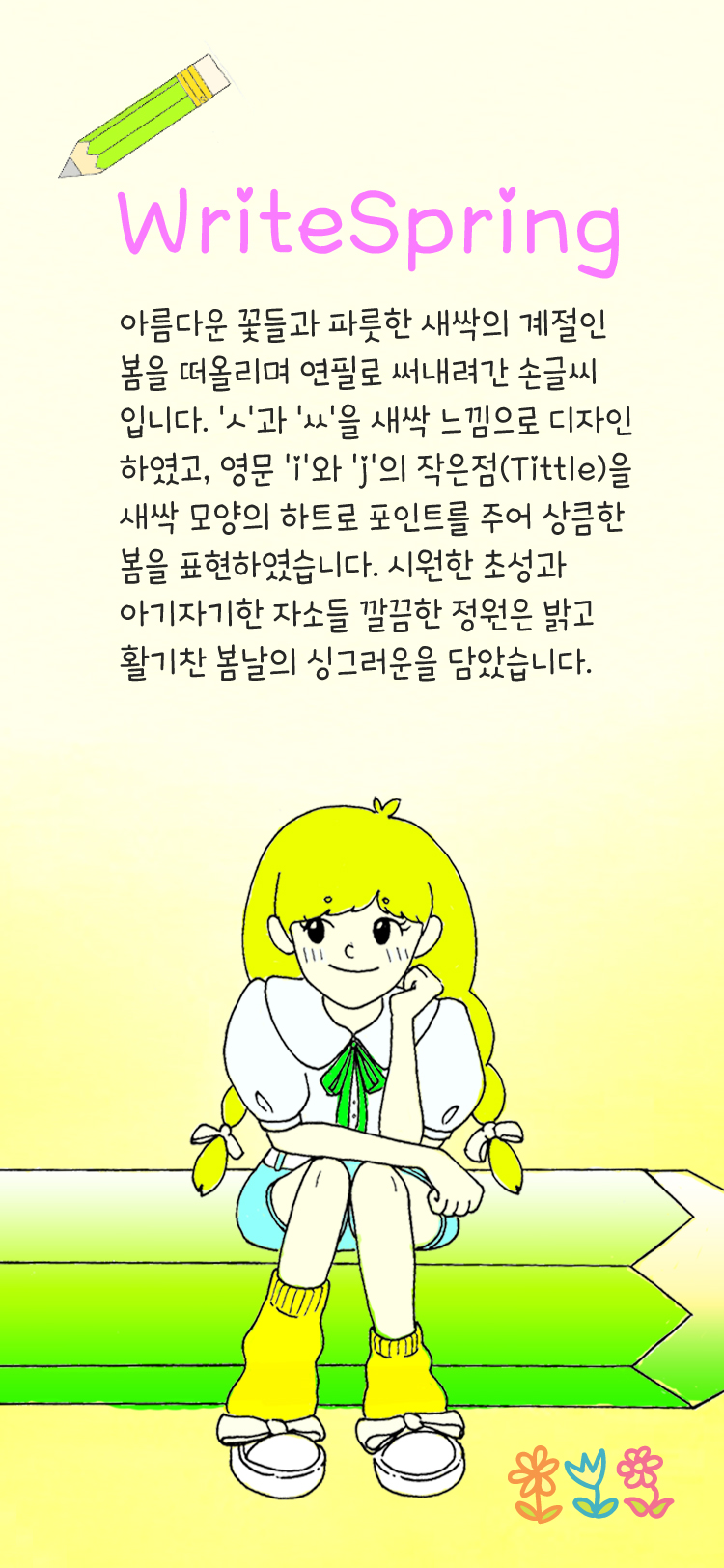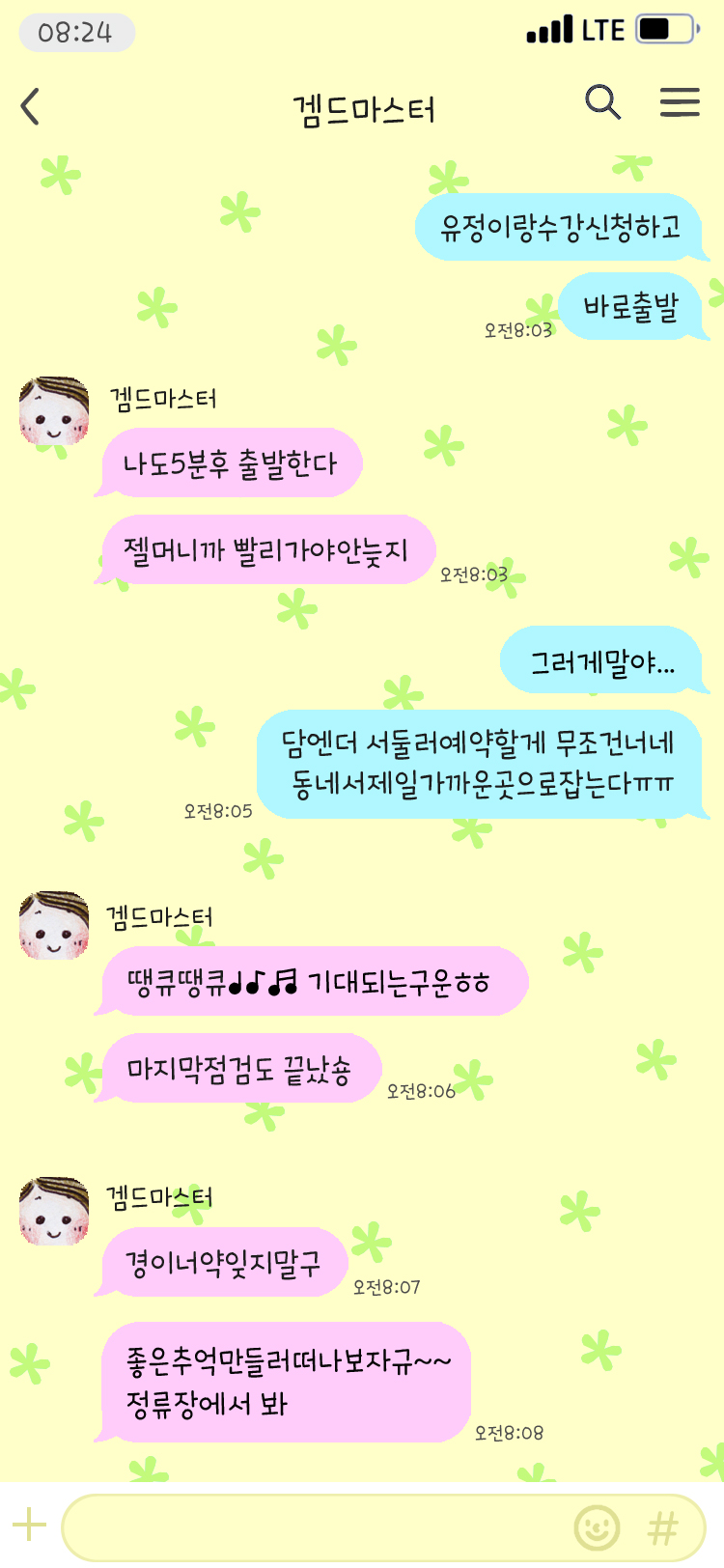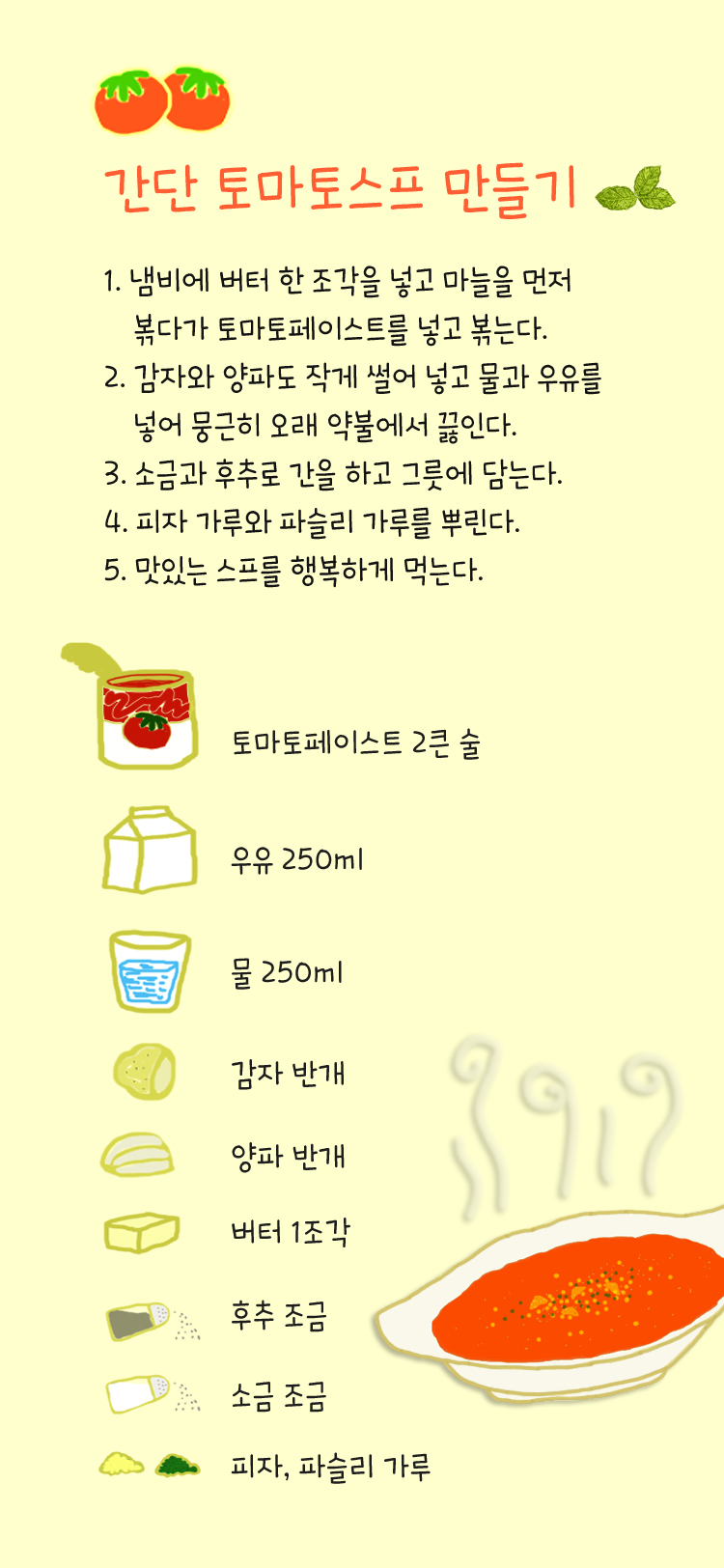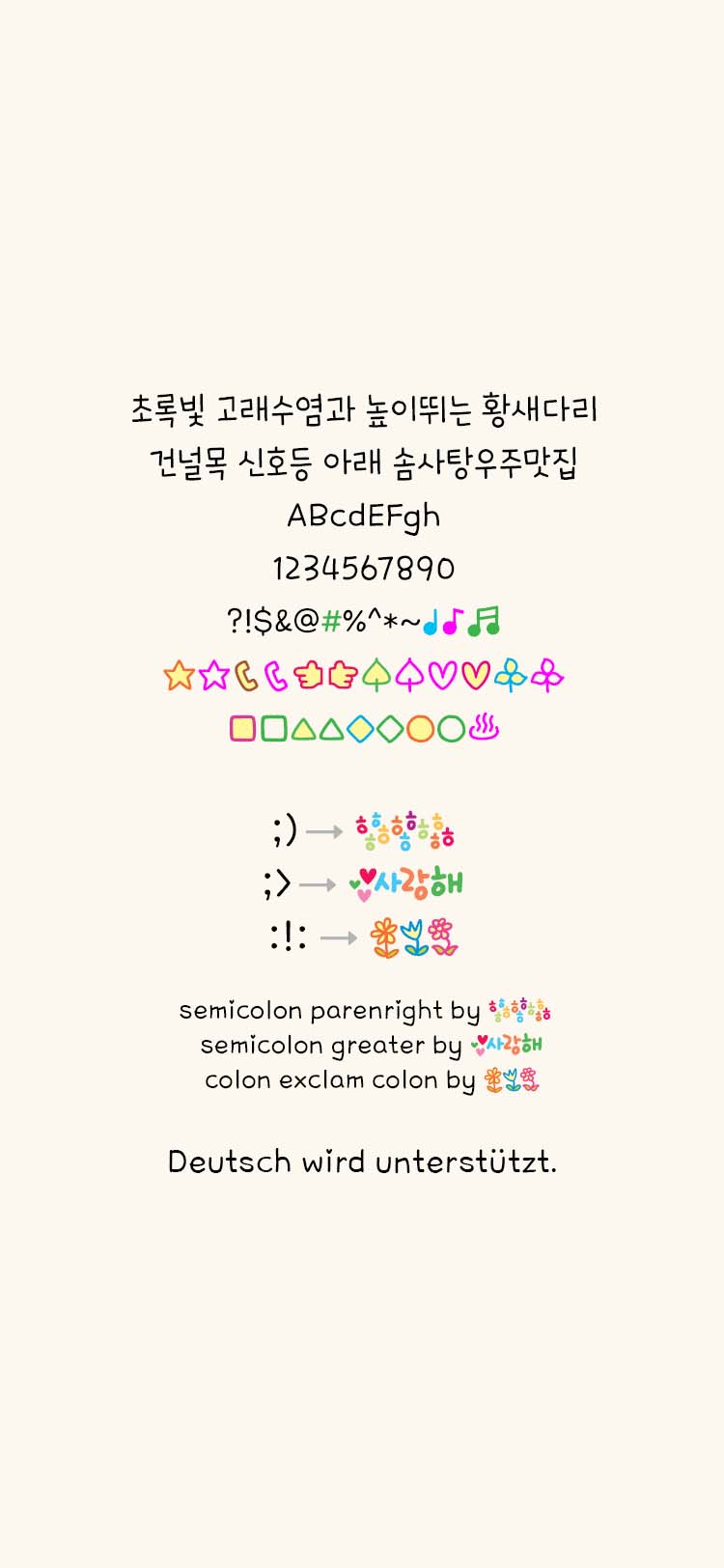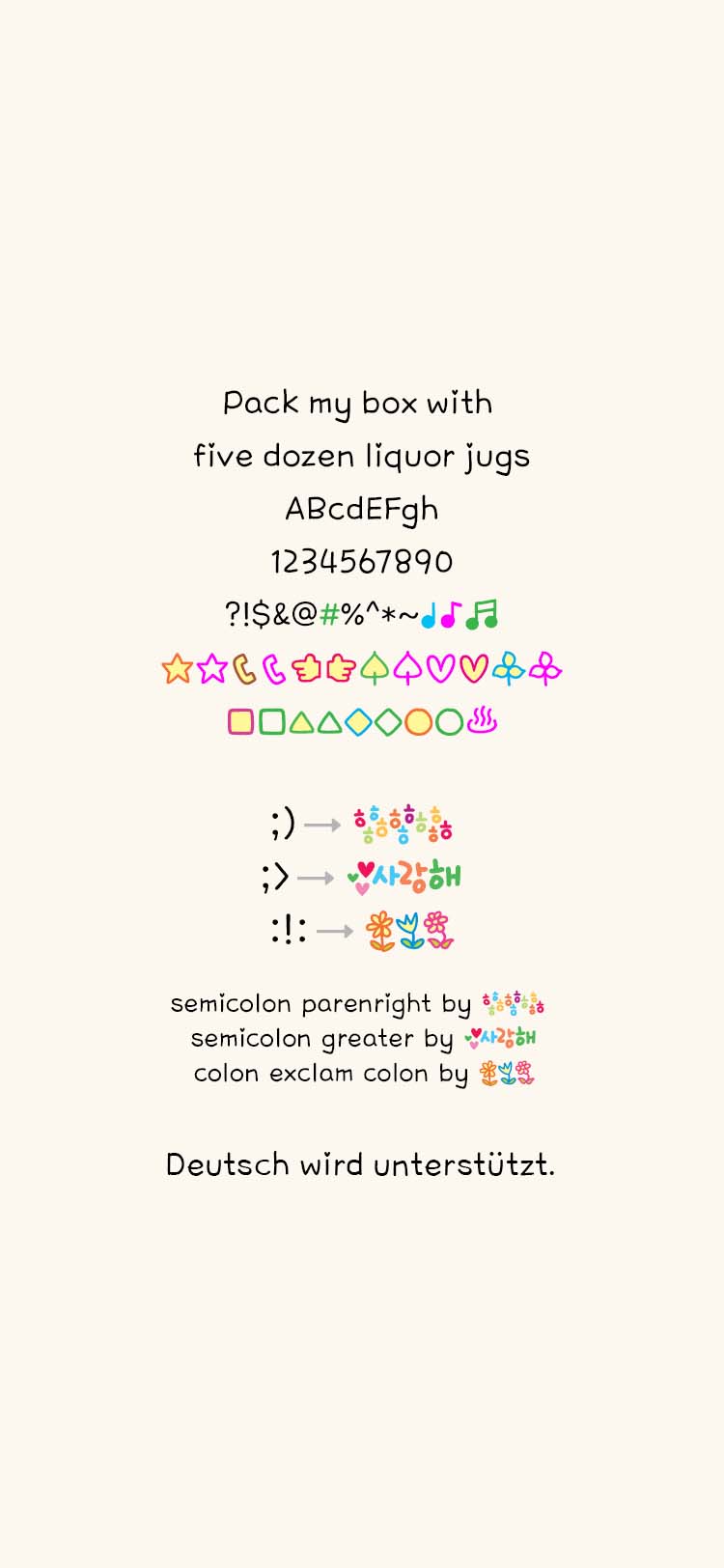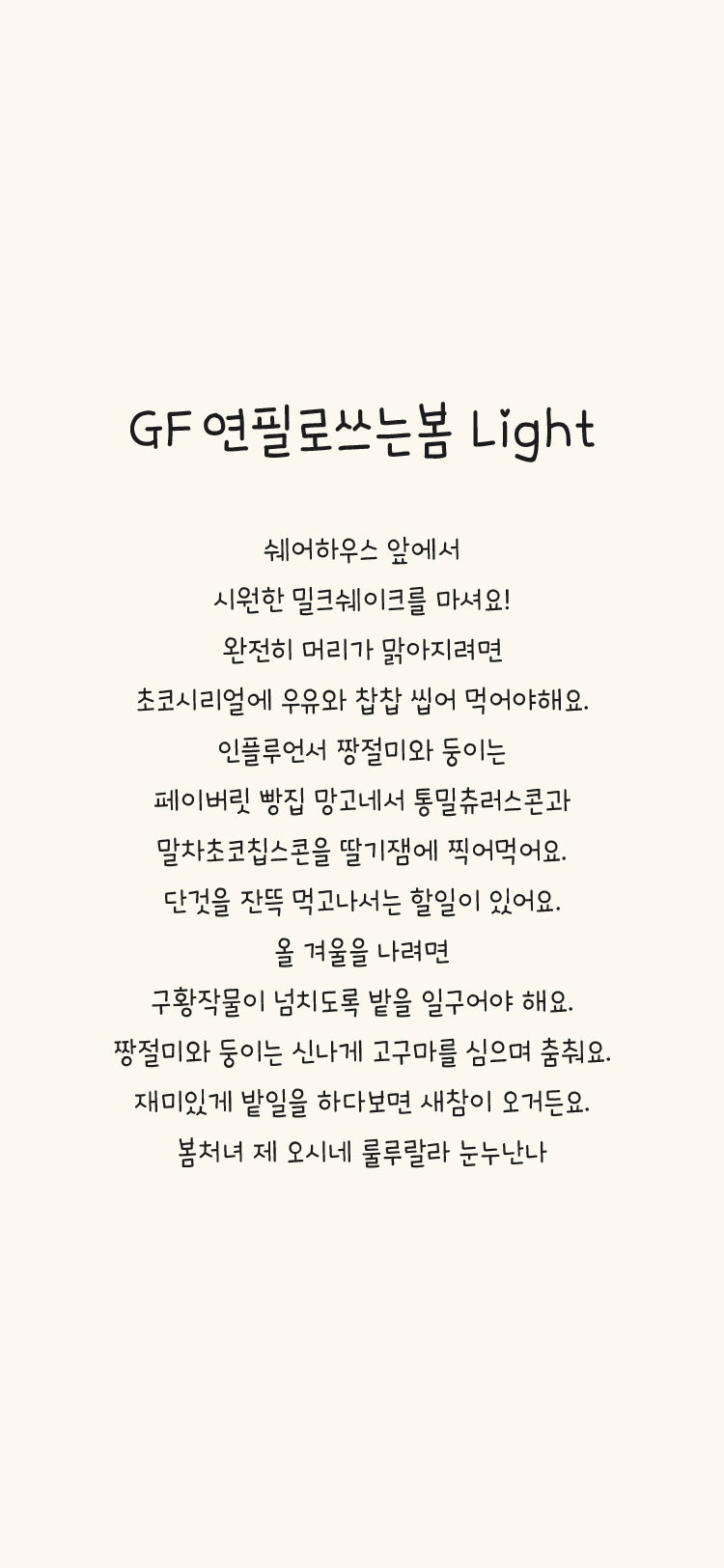
GF 연필로쓰는봄 M Light
아름다운 꽃들과 파릇한 새싹의 계절인 봄을 떠올리며 연필로 써내려간 손글씨 입니다. 'ㅅ'과 'ㅆ'을 새싹 느낌으로 디자인 하였고, 영문 'i'와 'j'의 작은점(Tittle)을 새싹 모양의 하트로 포인트를 주어 상큼한 봄을 표현하였습니다. 시원한 초성과 아기자기한 자소들 깔끔한 정원은 밝고 활기찬 봄날의 싱그러운을 담았습니다.
semicolon parenright by ㅎㅎㅎ
semicolon greater by 사랑해
colon exclam colon by 꽃